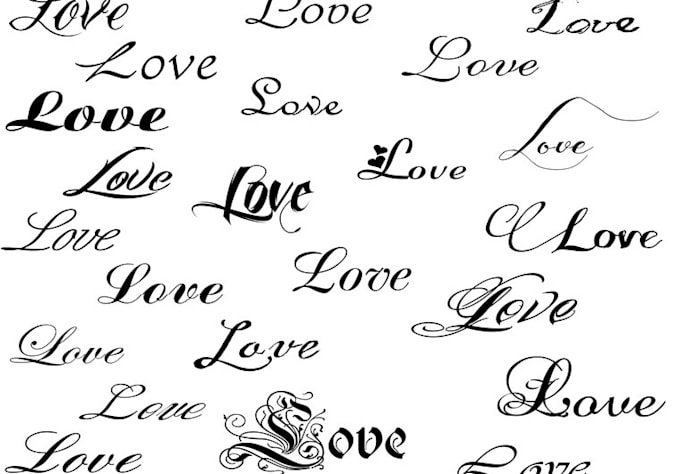
Красивые шрифты онлайн. напиши и скопируй 🤩
Работа с шрифтами в Figma
В Figma мало выбрать красивые, подходящие для вашей системы шрифты
Тут важно еще правильно задать интерлиньяж. К примеру, для заголовков и для основного текста он будет неодинаков
Далее описывается, от чего следует отталкиваться в каждом из этих случаев.
Параметры основного текста.
Главное требование к типографике основного текста – хорошая читаемость. Для этого можно немного увеличить межстрочное расстояние. Слишком плотный текст воспринимается труднее. Как выбрать оптимальный интерлиньяж для основного текста? Умножьте размер шрифта на 1,5, и посмотрите, какой вид в результате получится у текста.
Влияние оптических эффектов.
Цвета текста и фона тоже имеют значение при определении интерлиньяжа. Положительный и негативный тексты (то есть, темные буквы на светлом фоне и наоборот, соответственно) смотрятся и читаются неодинаково. На восприятие влияет контекст и оптические эффекты, даже если свойства стиля оставить неизменными.
Влияние оптических эффектов
К примеру, в Figma можно установить шрифт и стиль специально для положительного либо отрицательного текста. Разница тут будет в том, что для темного фона применяется чуть большее расстояние между буквами.
Оформление заголовков.
Здесь не понадобится такое же большое межстрочное и межбуквенное пространство, как в основном тексте. В заголовке вы, скорее всего, захотите уменьшить интервал между строками. Возможно, выбранный шрифт представлен в нескольких вариантах (с расчетом на корректное отображение в устройствах с дисплеями разных размеров), и разработчик уже целенаправленно уменьшил интервал, это заранее заложено, как элемент дизайна шрифта.
При установке шрифта в Figma можно порекомендовать выбирать размеры текста по принципу водопада, с переходом от большего к меньшему. Так вся система будет смотреться нагляднее и эстетичнее.
- Прописные;
- Каллиграфические;
- Печатные;
- Другие.
Но всё, что нужно знать с самого начала – что для того, чтобы набор поддерживал русские буквы, вам нужно выбрать только тот пак, где заявлена поддержка кириллицы. В этом случае любой текст на русском языке вы сможете открыть в новом виде. Если же у вас другая задача – английский текст, то тут все намного проще, так как латиница поддерживается практически любой сборкой, ведь английский является универсальным языком.
Подробное руководство по лучшим бесплатным шрифтам • Beautiful Web Type
Испытайте себя совершенно новым.
Интер от Расмуса Андерссона
Стать мудрымCrimson Pro от Жака Ле Байи
Мессапия, Лука Марсано
Космический Гротеск Флориана Карстена
Мацуо Басё
iA Writer Quattro от iA
Код Fira Никиты Прокопова
Space Mono от Colophon Foundry
Fivo Sans от Алекса Слобженинова
Фиво Санс Модерн от Алекса Слобженинова
Мессапия Интер
Фраунс Либре Франклин